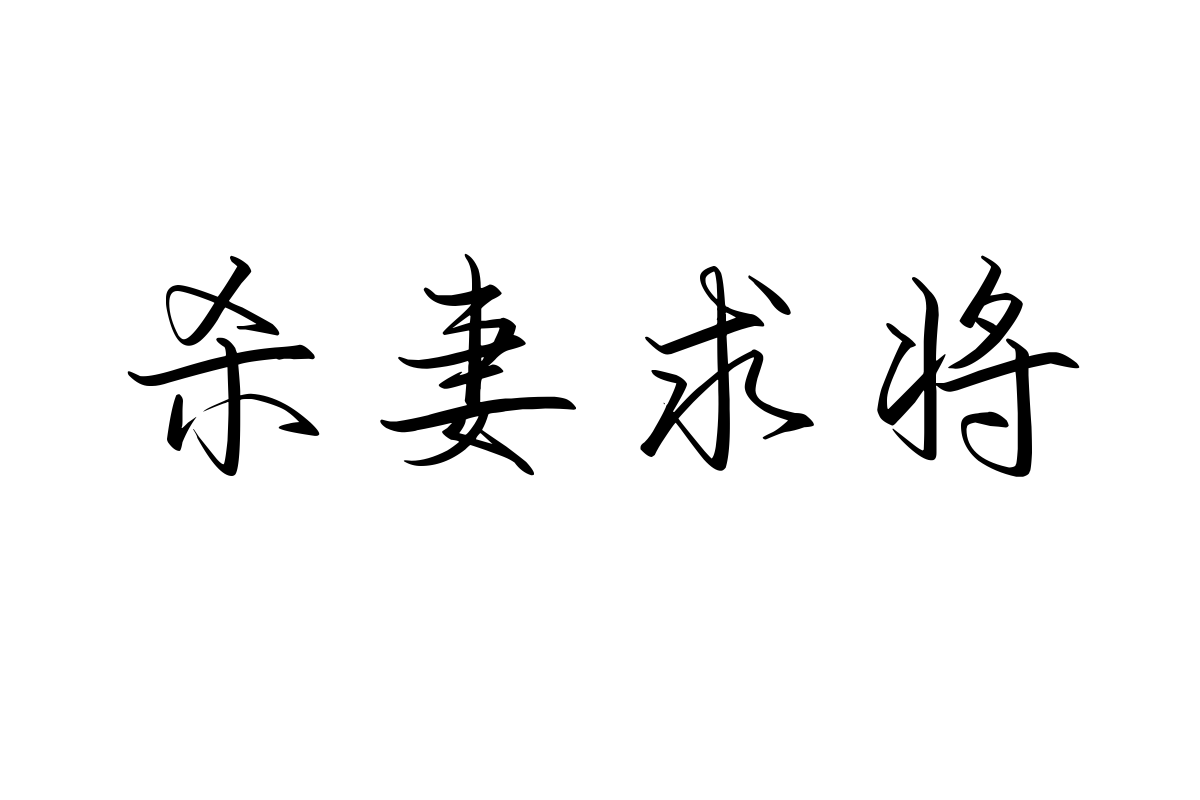
也字工厂醉寒江行草字体是一种具有独特风格和艺术感的手写体,由也字工厂设计。这款字体采用了传统的行草书风格,将笔画进行简化和变形,使其更加流畅自然。同时,也字工厂醉寒江行草字体还融入了一些现代元素,使得整体看起来更加时尚和现代。
这款字体适用于各种需要手写风格的场合,如书法、名片、海报等。它的笔画流畅自然,给人一种轻松愉悦的感觉,非常适合用来表达个人情感和创作独特的艺术作品。